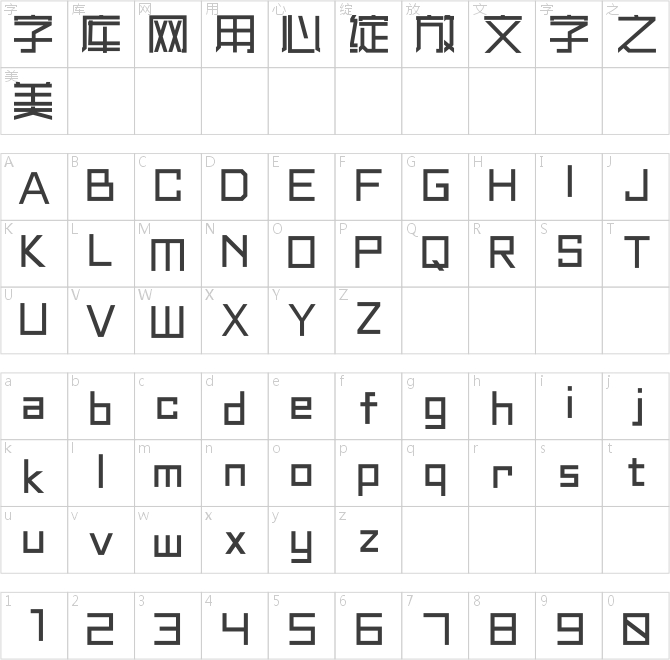
漢儀后現(xiàn)代
漢儀/劉痕
漢儀后現(xiàn)代字體HYHouXianDaiW字庫(kù)是一款讓人賞心悅目、百看不厭的中文字體,適合各類(lèi)廣告和產(chǎn)品包裝設(shè)計(jì)應(yīng)用,字體大小1.93MB,格式為ttf字體,上傳用戶(hù)是Apple,作者/版權(quán)方為漢儀/劉痕